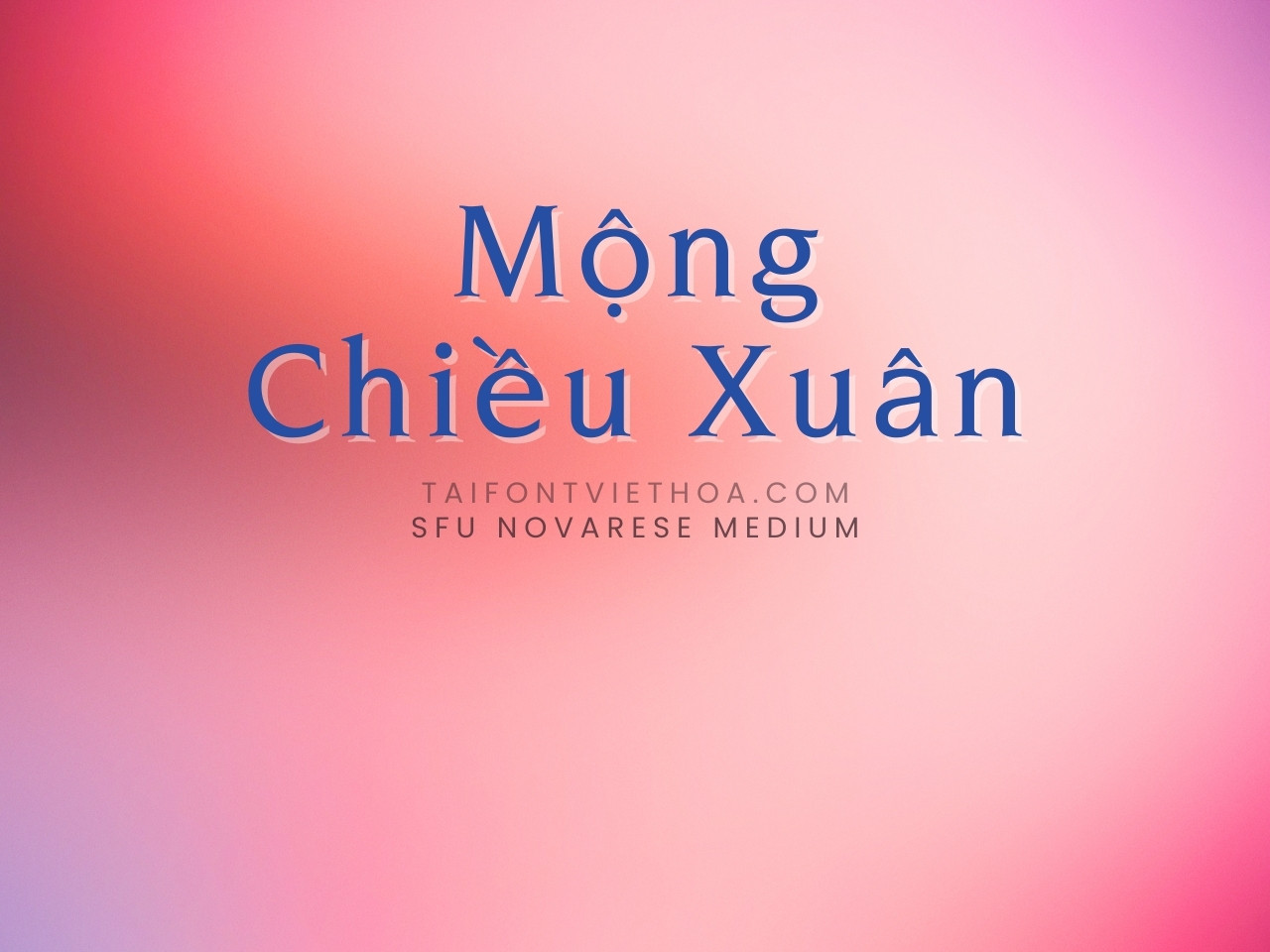
Font việt hóa SFU Novarese
Giới thiệu font SFU Novarese – Kiệt tác chữ cổ điển từ Aldo Novarese
SFU Novarese là phiên bản Việt hóa từ bộ font nổi tiếng Novarese, được thiết kế bởi huyền thoại người Ý Aldo Novarese và phát hành vào năm 1978 bởi hãng fonderie Nebiolo. Font mang theo dấu ấn của thời kỳ chuyển giao giữa cổ điển và hiện đại, với các đường nét thanh lịch, mạnh mẽ nhưng vẫn mềm mại. Phiên bản SFU đã Việt hóa đầy đủ dấu tiếng Việt, mở rộng khả năng ứng dụng cho người dùng Việt Nam và vẫn giữ nguyên giá trị hình thức ban đầu. Ngoài ra, Novarese còn hỗ trợ hơn 100 ngôn ngữ quốc tế – phù hợp cho các dự án đa ngôn ngữ và xuất bản chuyên nghiệp.
Font này được taifontviethoa.com chọn lọc và giới thiệu như một phần trong bộ sưu tập font serif cổ điển cao cấp. Với chất lượng thiết kế ổn định, chuẩn mực và khả năng thể hiện rõ ràng, SFU Novarese không chỉ là một công cụ thiết kế mà còn là một biểu tượng của nghệ thuật typography, đặc biệt phù hợp cho những dự án đòi hỏi sự chuẩn chỉnh và đẳng cấp về mặt hình thức.
Thiết kế chữ tinh xảo, tối ưu cho in ấn và xuất bản
SFU Novarese sở hữu cấu trúc chữ serif mạnh mẽ với các nét gãy gọn, độ tương phản vừa phải giữa nét đậm – nét mảnh, mang lại cảm giác cổ điển nhưng không nặng nề. Những chi tiết như chân chữ, vòng tròn mở và chiều cao chữ cái cân đối giúp font dễ đọc, ngay cả trên khổ nhỏ. Phần gạch chân mềm mại và độ dốc chữ nhẹ cũng tăng tính linh hoạt khi dùng cho nội dung dài.
Font lý tưởng cho các ứng dụng như: thiết kế tạp chí, sách in, danh mục sản phẩm, bản thảo văn học, bao bì mỹ phẩm hoặc thương hiệu cao cấp. Các ngành phù hợp gồm: xuất bản, giáo dục, truyền thông, mỹ thuật, thời trang và đặc biệt là quảng cáo cao cấp. SFU Novarese giúp tạo dựng bản sắc chữ viết chuyên nghiệp, dễ đọc và đậm tính thẩm mỹ – thích hợp cho mọi nhà thiết kế cần sự cân bằng giữa nghệ thuật và công năng.